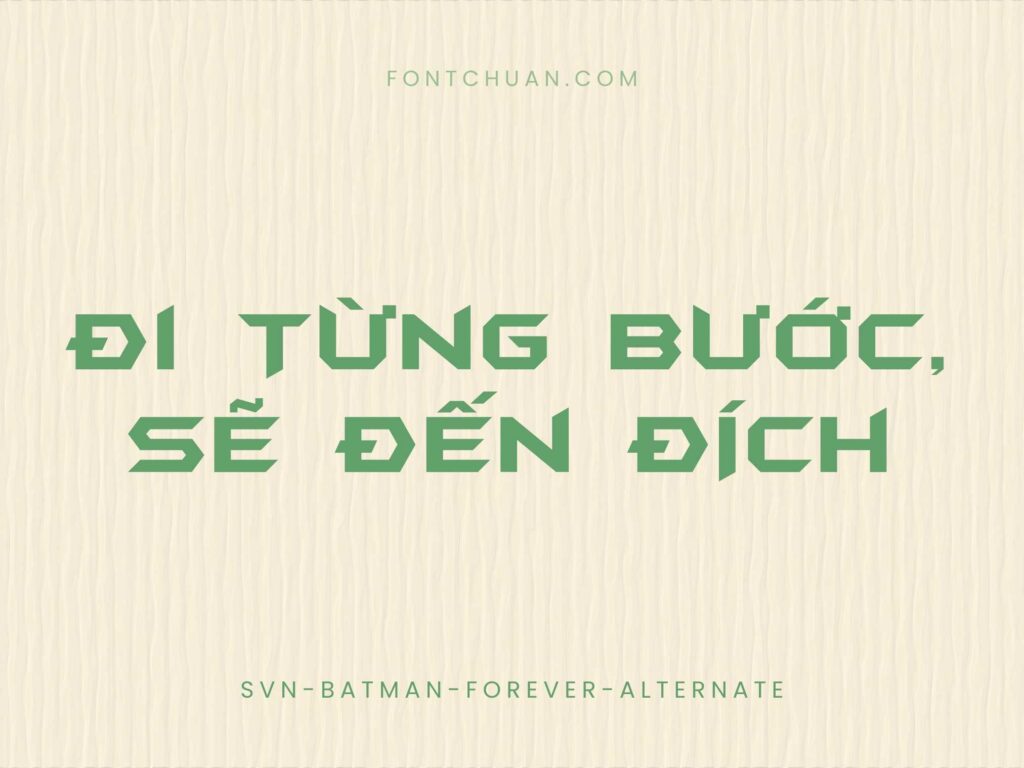
Font SVN Batman Forever Alternate Việt Hóa
Batman Forever Alternate là một font chữ được lấy cảm hứng từ logo của bộ phim “Batman Forever” phát hành năm 1995. Font này thuộc thể loại khoa học viễn tưởng, mang phong cách hiện đại và mạnh mẽ, phù hợp cho các thiết kế liên quan đến chủ đề siêu anh hùng và công nghệ. Font đã được Việt hóa để hỗ trợ tiếng Việt bởi Styleno.1 Fonts, đồng thời hỗ trợ nhiều ngôn ngữ khác, giúp mở rộng phạm vi sử dụng trên toàn cầu. Font này được thành viên của Font Chuẩn sưu tầm và chia sẻ, đáp ứng nhu cầu của bạn đọc và ứng dụng thực tế vào các dự án thiết kế.
Đặc điểm thiết kế của Batman Forever Alternate bao gồm các đường nét góc cạnh, sắc sảo và hiện đại, tạo cảm giác mạnh mẽ và năng động. Font này phù hợp cho các ứng dụng như thiết kế poster, tiêu đề phim, bìa sách, logo và các dự án sáng tạo khác. Các ngành nghề phù hợp bao gồm quảng cáo, giải trí và công nghệ.